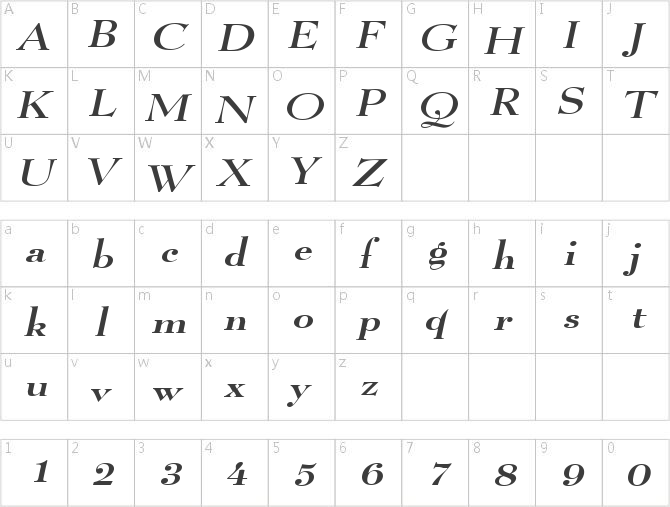
字體名稱(chēng): Luciano
Luciano-Wide-Italic
Luciano-Wide-Italic字體字庫(kù)是一款讓人賞心悅目、百看不厭的英文字體,適合各類(lèi)廣告和產(chǎn)品包裝設(shè)計(jì)應(yīng)用,字體大小0.07MB,格式為ttf字體,上傳用戶(hù)是ㄚòひ慬偶鰢,作者/版權(quán)方為未知